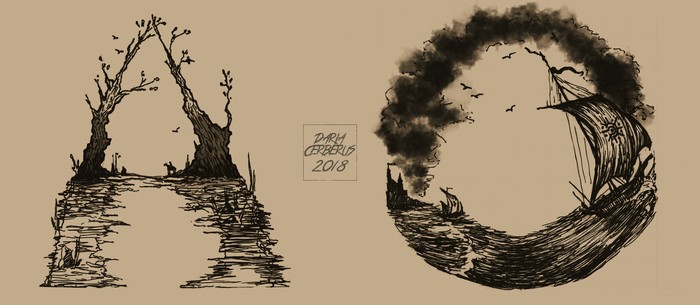
«Авторский шрифт»
Всем привет! Решила поделиться с вами своим рисованным шрифтом — заданием с прошлого курса в институте. Сказали нам сделать оригинальный шрифт с персонажами или чем-нибудь красивым. Пока одногруппники делали собачек-змеек, я ударилась в другое:
В поисках вдохновения наткнулась на один вариант латинских букв с пейзажами, и именно он натолкнул меня на эту идею. Плюсом ко всему, я из тех людей, у которых в голове есть свои персонажи и своя мир (с детства люблю это дело), поэтому шрифт я делала с опорой на свою выдуманную вселенную, что превратило работу в удовольствие
Виселицу на букве Б мне предложила сделать преподаватель 👌🏻 :D
После этого задания я втянулась в рисование чернилами и линерами, графика полюбилась ещё больше. Пусть этот шрифт нельзя использовать для написания цельных слов, но зато его можно заюзать как, например, буквицу (чем я и займусь когда-нибудь)